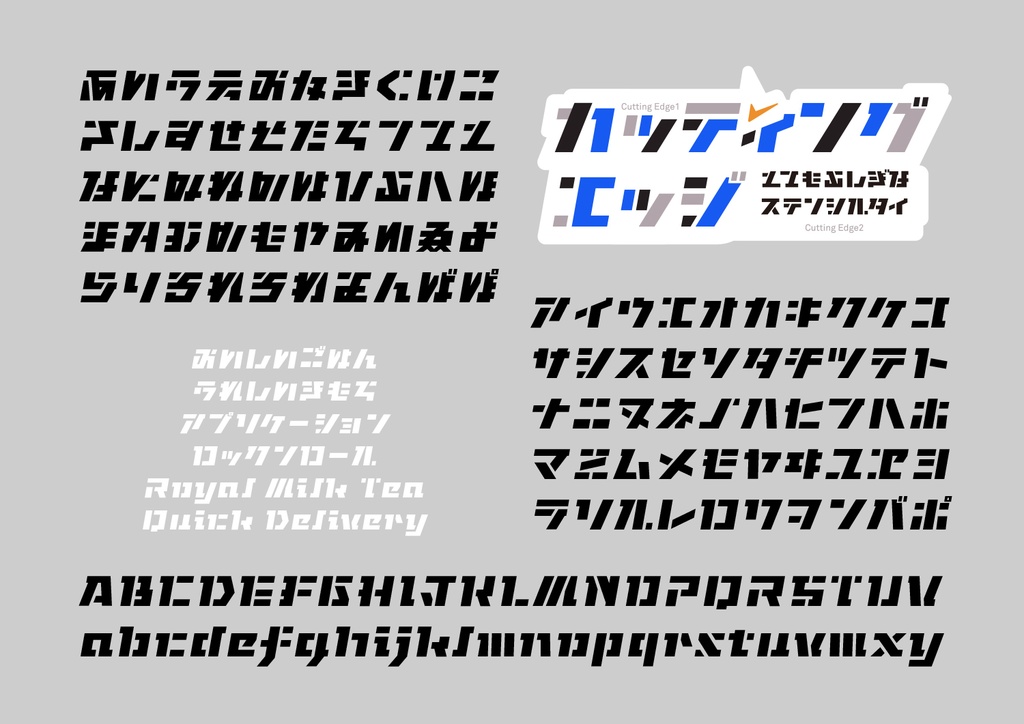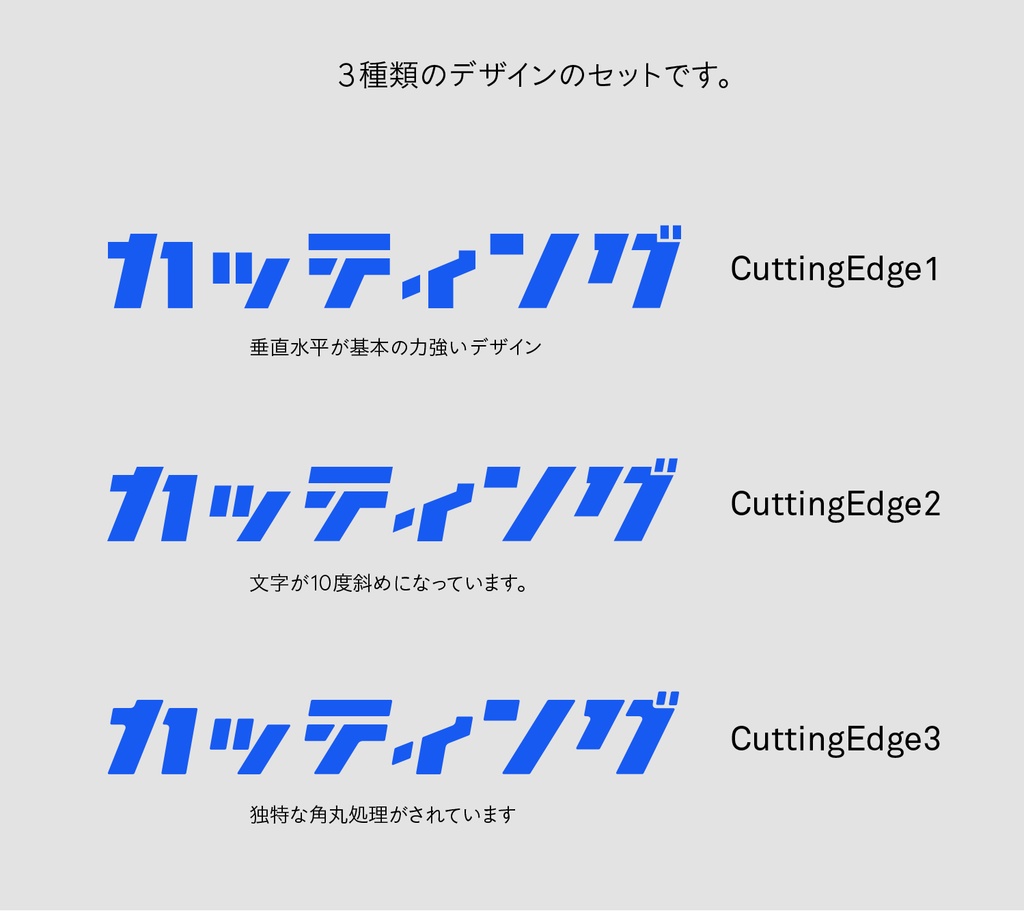
カッティングエッジ フォント
ステンシル体っぽいデザインの斬新なロゴ用のフォントです。3種類のデザイン収録。 動作環境 Mac:システム/OS X対応(10.x)〜最新のOS X Windows:OS/日本語版Windows2000、XP、VISTA、Windows7、Windows8、Windows10、Windows11以降 フォント形式:OpenTypeフォント 収録文字数について アルファベット、カタカナ、ひらがな、記号の一部のみの書体になります。 安心して使えるロイヤリティフリーの書体 あらゆる商用・デザイン用途(印刷物・ゲーム・アプリ・映像・動画・ロゴ・同人作品)に使用できる、商用申請の必要のないロイヤリティフリーの書体になります。文字の加工・変形も可能です。ご安心ください。 個性的なデザインに注目した日本語フォントのダウンロード販売。安心して使える商用利用可のオリジナルフォントです。